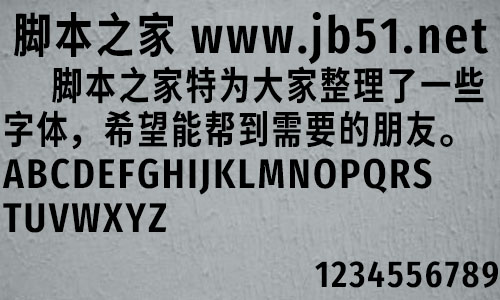
未來(lái)熒黑狹中字體是未來(lái)熒黑系類字體中的其中一款,該字體由八種字重,字體中宮與字面更加收斂,細(xì)節(jié)上面處理更加的干練,適合應(yīng)用于藝術(shù)設(shè)計(jì)、平面宣傳設(shè)計(jì)、網(wǎng)頁(yè)設(shè)計(jì)等領(lǐng)域,有需要的朋友可以下載使用哦!
未來(lái)熒黑是一個(gè)基于思源黑體、Fira Sans和Raleway的開(kāi)源字體項(xiàng)目,支持簡(jiǎn)體中文、繁體中文與日文;思源黑體的7字重被擴(kuò)展為9字重,并提供了寬度系列,全家族共44款字體。
相比于思源黑體,未來(lái)熒黑的造型更加簡(jiǎn)明現(xiàn)代,版面效果清新輕快。未來(lái)熒黑的中宮與字面更加收斂,重心在字重之間經(jīng)過(guò)了重新配置;筆畫細(xì)節(jié)上處理得更加干練,簡(jiǎn)潔而平直化。您可以下載樣張來(lái)預(yù)覽未來(lái)熒黑的設(shè)計(jì)。
未來(lái)熒黑的實(shí)現(xiàn)介于參數(shù)化與輪廓濾鏡,使用了圖像處理算法對(duì)字形建模。字體的制作并沒(méi)有借助字體設(shè)計(jì)軟件,而是用一個(gè)Web實(shí)現(xiàn)的可視化調(diào)參工具來(lái)確定字體參數(shù)